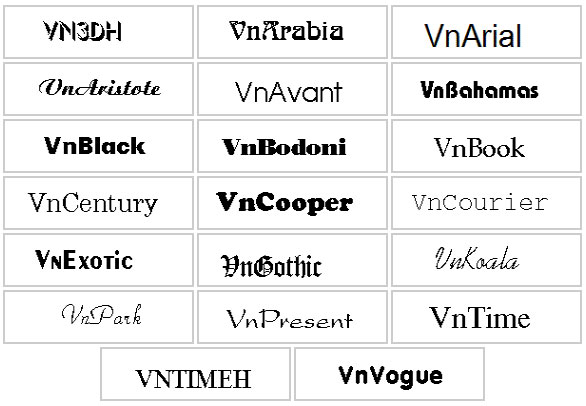
Bộ font TCVN3 (hay còn gọi là phông chữ ABC) đóng vai trò nền tảng trong việc xử lý các văn bản và bản vẽ kỹ thuật sử dụng bảng mã cũ tại Việt Nam. Dù hiện nay Unicode đã trở nên phổ biến, việc download font TCVN3 vẫn là nhu cầu thiết yếu để hiển thị chính xác nội dung trong các hồ sơ lưu trữ, dự toán hoặc bản vẽ AutoCAD từ những thập niên trước.
Đặc trưng của hệ thống phông chữ TCVN3 trong công việc chuyên môn
Điểm nhận diện đặc trưng của dòng phông này chính là các tên font luôn bắt đầu bằng tiền tố “.Vn” (ví dụ: .VnTime, .VnArial). Khác với bảng mã Unicode hiện đại, tải font chữ TCVN3 cung cấp khả năng tương thích cao với các phần mềm chuyên ngành đời cũ vốn chưa hỗ trợ tốt các chuẩn ký tự mới. Cấu trúc của bộ chữ được thiết kế tinh gọn, giúp văn bản hiển thị rõ nét trên các hệ máy tính cấu hình thấp hoặc các dòng máy in truyền thống mà không gặp tình trạng lỗi dấu thanh.
Sự ổn định của TCVN3 còn thể hiện ở tính đồng bộ trong các biểu mẫu hành chính và hồ sơ pháp lý cũ. Việc sở hữu tải bộ font TCVN3 đầy đủ giúp bạn tránh được các lỗi nhảy chữ, mất ký tự khi mở các tệp tin quan trọng từ đối tác hoặc cơ quan nhà nước. Đây là giải pháp tin cậy để duy trì tính toàn vẹn của thông tin kỹ thuật, hỗ trợ đắc lực cho quá trình tra cứu và thực hiện các dự án cải tạo nhà lắp ghép, văn phòng container từ khung cũ một cách chuyên nghiệp.
Hồ sơ tải full font TCVN3 bao gồm hàng trăm kiểu chữ khác nhau, từ các mẫu phông đứng, phông đậm đến các kiểu phông hoa dùng cho tiêu đề trang trọng. Dưới đây là thông số chi tiết để bạn tham khảo.
| Phân loại bảng mã | TCVN3 (ABC) – Tiêu chuẩn Việt Nam 3 |
| Tiền tố nhận diện | Bắt đầu bằng “.Vn” hoặc “.VN” |
| Dòng font tiêu biểu | .VnTime, .VnArial, .VnCourier, .VnUniverse |
| Mục đích phù hợp | Đọc file cũ, hồ sơ dự toán, bản vẽ AutoCAD |
Tư vấn kỹ thuật: Khi sử dụng tải font TCVN3 đầy đủ, bạn cần điều chỉnh bảng mã trên Unikey sang mục “TCVN3 (ABC)” để gõ được tiếng Việt. Đối với các tiêu đề cần nhấn mạnh, hãy ưu tiên chọn các font kết thúc bằng chữ “H” (như .VnTimeH) để có độ đậm ổn định cho bản in.
03 Ứng dụng thực tế cần sử dụng tải font chữ TCVN3
Nhờ tính kế thừa lâu đời, việc sử dụng các kiểu chữ từ bộ tải fonts TCVN mang lại giá trị thực tế cao trong quá trình triển khai công việc ngành xây dựng:
- Xử lý chú thích trên bản vẽ CAD cổ: Nhiều bản vẽ kết cấu thép, sơ đồ panel từ những năm 2000 sử dụng tải font cad TCVN3 để ghi chú. Việc cài đặt font này giúp các thông số hiển thị minh bạch, hỗ trợ đội ngũ thi công nắm bắt chính xác ý đồ thiết kế.
- Làm việc với bảng tính dự toán cũ: Các tệp Excel quản lý vật tư hay báo giá thi công nhà lắp ghép sử dụng bảng mã ABC yêu cầu bộ font này để không bị lỗi “ô vuông”, giúp việc quản lý ngân sách dự án diễn ra trôi chảy.
- Đồng bộ hồ sơ pháp lý nhà đất: Các văn bản giấy phép xây dựng hoặc tài liệu quy hoạch cũ thường dùng .VnTime. Sử dụng đúng bộ font giúp bạn trích xuất dữ liệu chỉn chu và chuyên nghiệp.
03 Lưu ý để sử dụng tải bộ font TCVN3 full không bị lỗi hiển thị
Để khai thác hiệu quả và hạn chế rắc rối khi làm việc với dòng font đặc thù này, người thiết kế nên lưu tâm một số kinh nghiệm sau:
- Phân biệt font chữ thường và font chữ đậm: Các font TCVN3 thường phân tách rõ ràng thành hai tệp riêng biệt cho kiểu thường và kiểu đậm (kết thúc bằng chữ H). Hãy cài đặt đủ cả hai để hồ sơ năng lực của bạn có sự phân cấp thông tin rõ ràng.
- Hạn chế dùng trong thiết kế web hiện đại: Font TCVN3 không hỗ trợ tốt cho hiển thị trên các trình duyệt web đời mới. Bạn nên sử dụng phông chữ này chủ yếu cho các phần mềm văn phòng offline hoặc in ấn hồ sơ nội bộ.